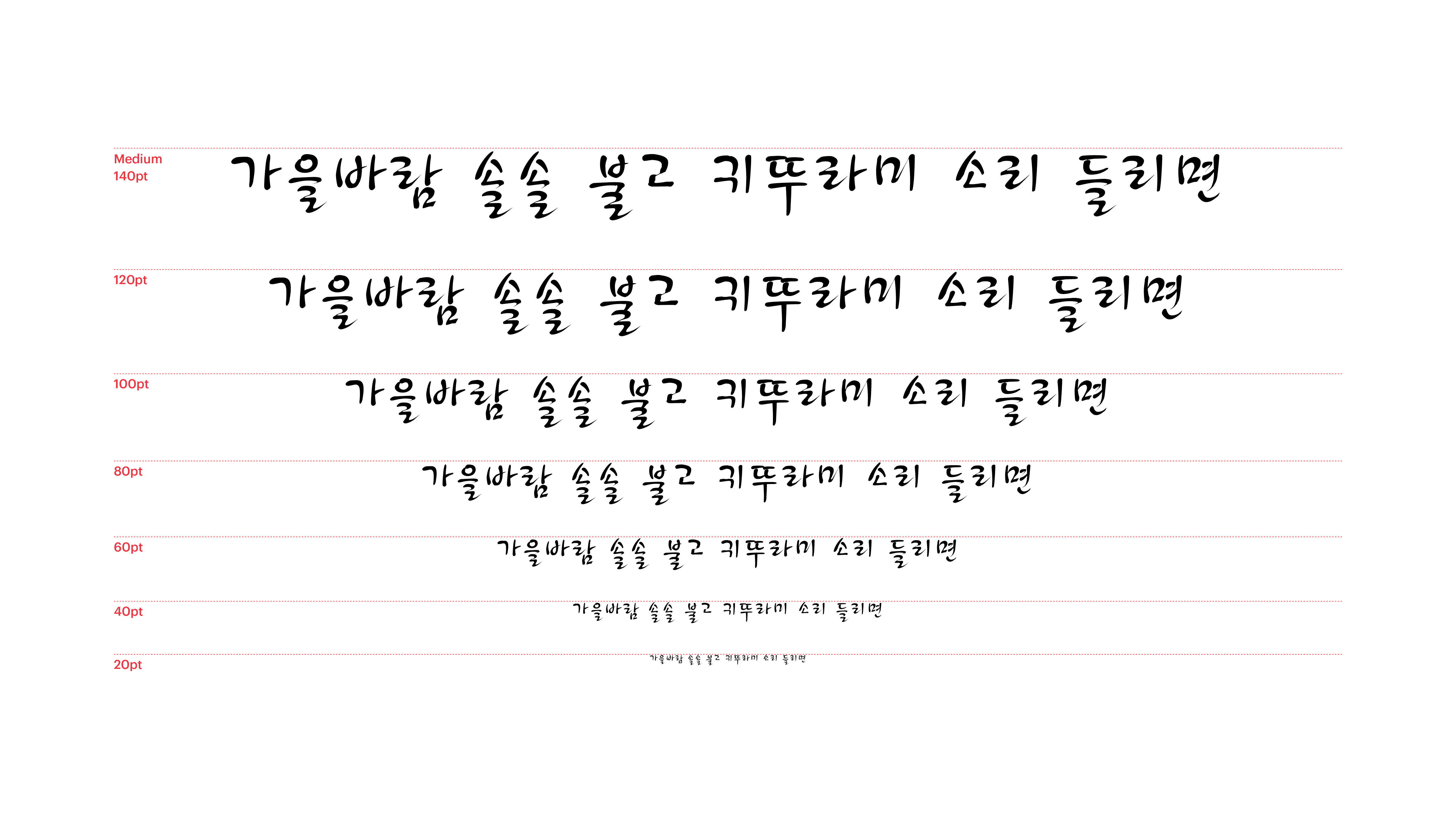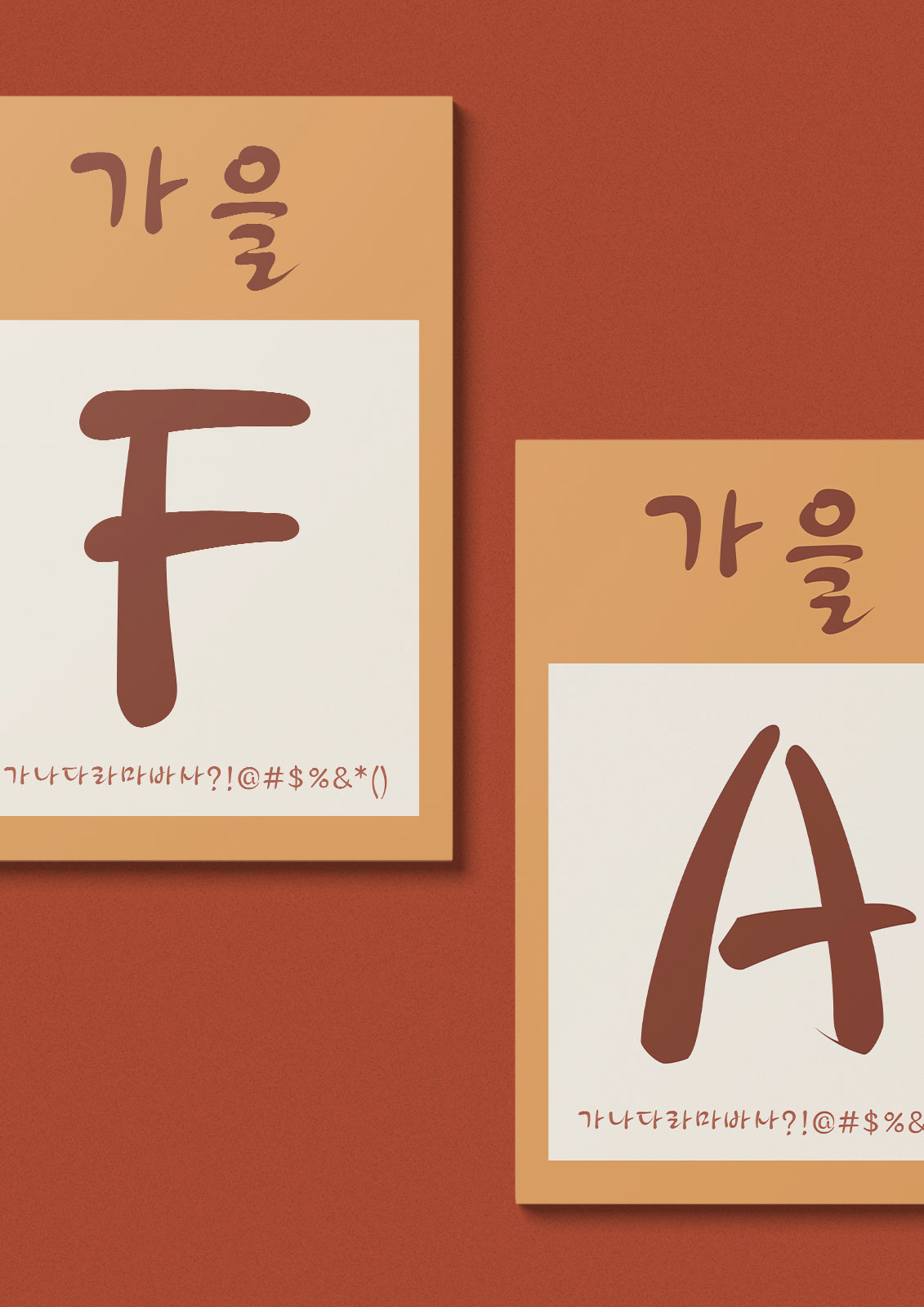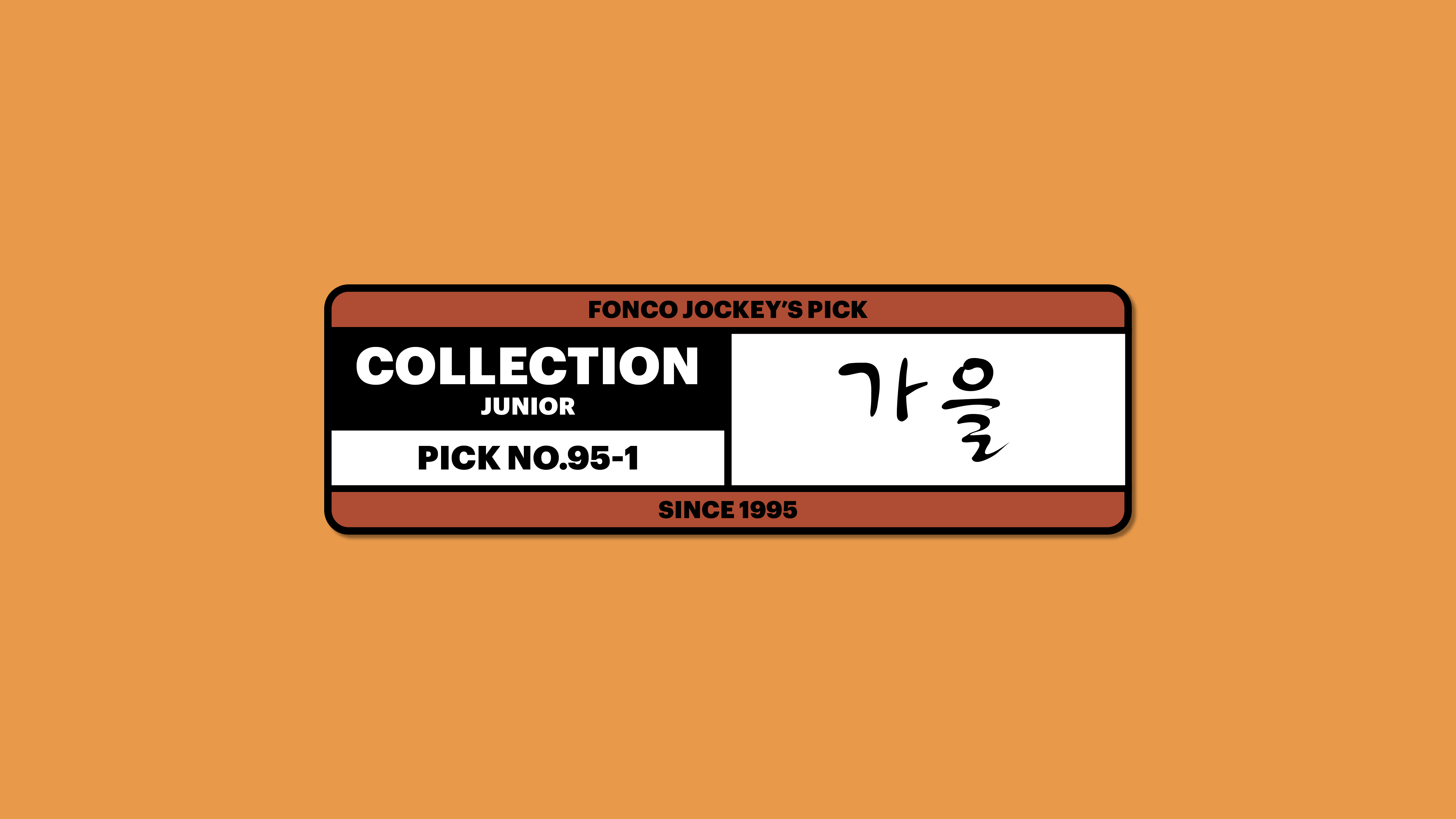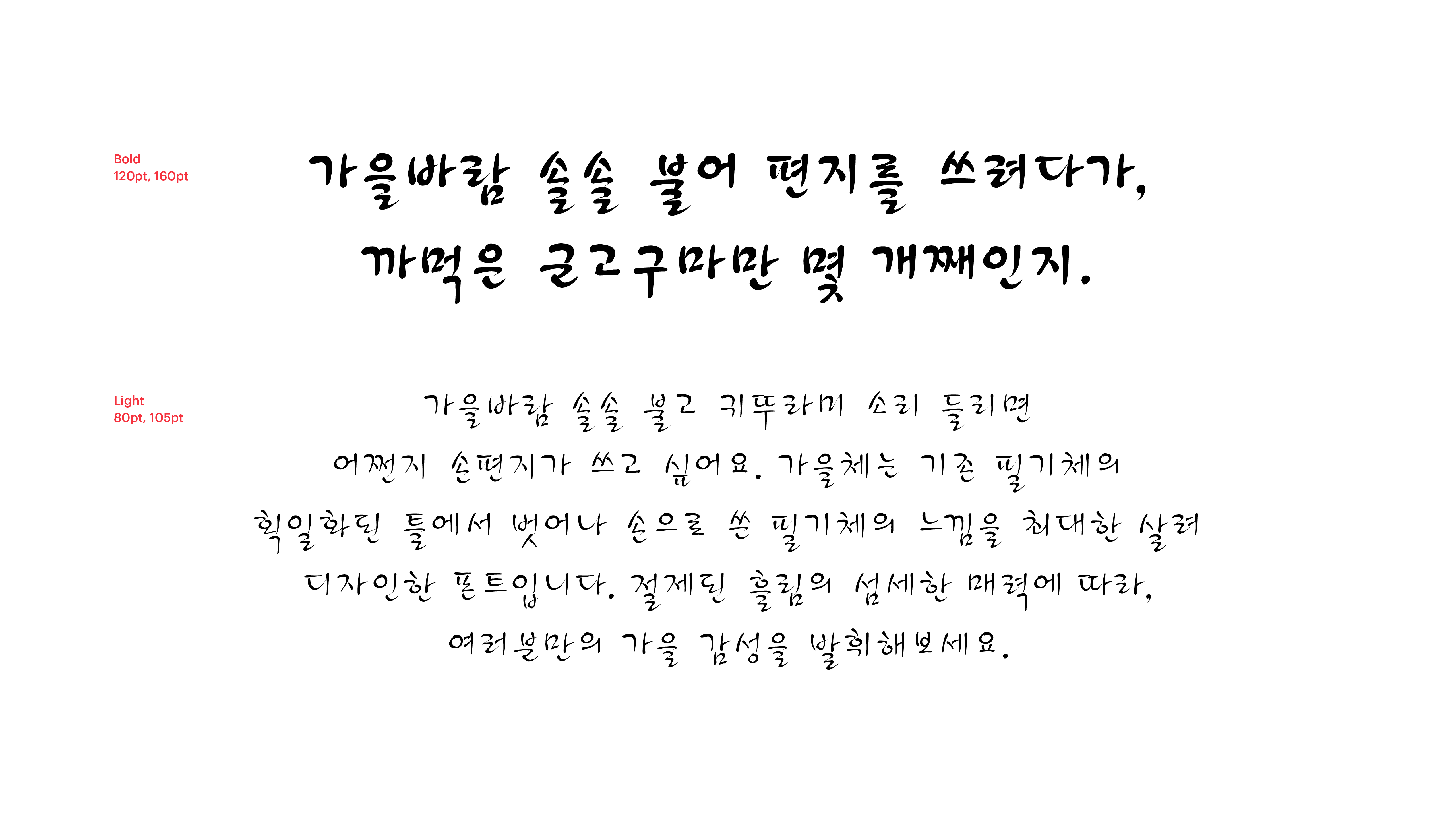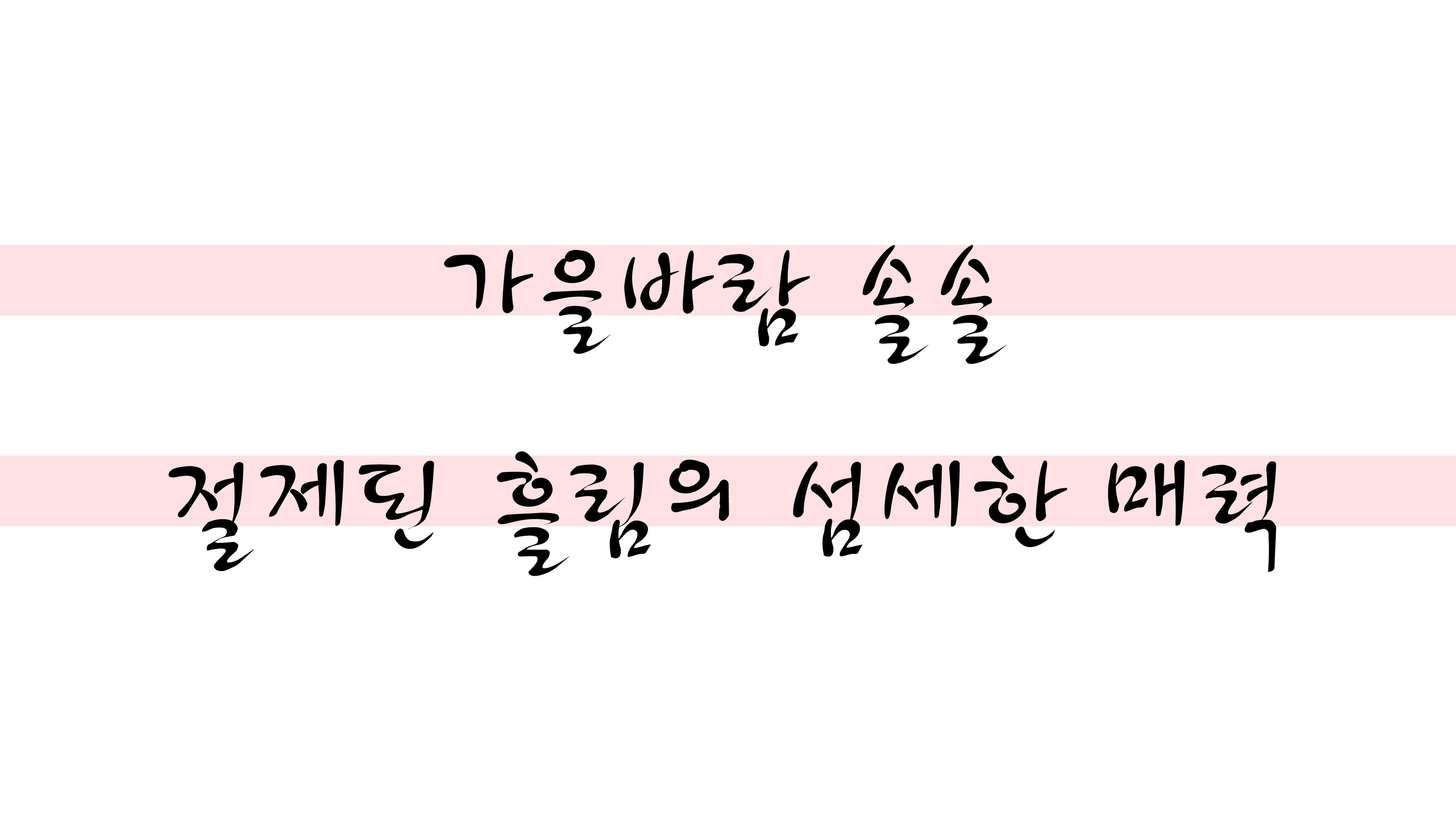
가을
Yoon 가을
가을바람 솔솔 불고 귀뚜라미 소리 들리면 어쩐지 손편지가 쓰고 싶어요. 가을체는 기존 필기체의 획일화된 틀에서 벗어나 손으로 쓴 필기체의 느낌을 최대한 살려 디자인한 폰트입니다. 절제된 흘림의 섬세한 매력에 따라, 여러분만의 가을 감성을 발휘해보세요.